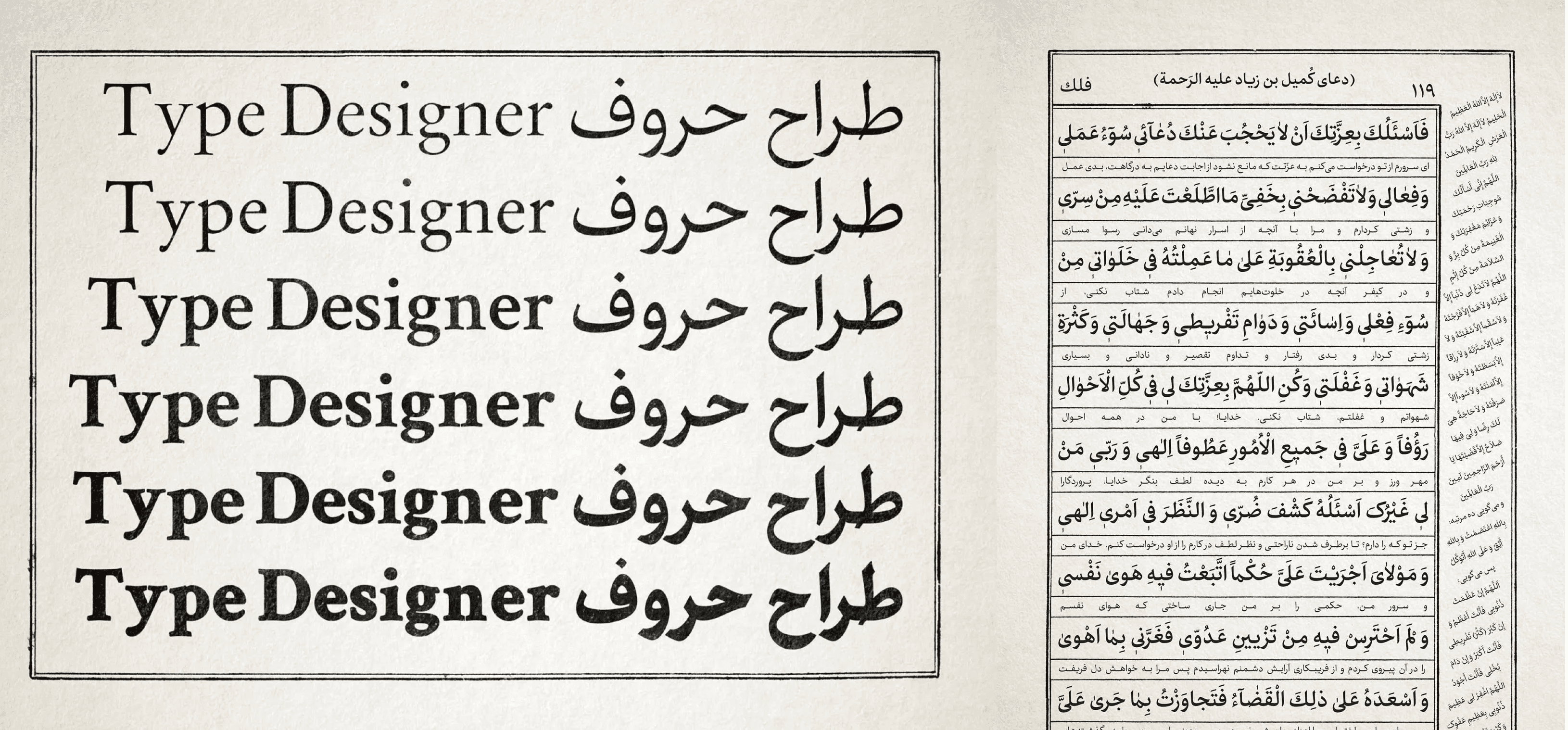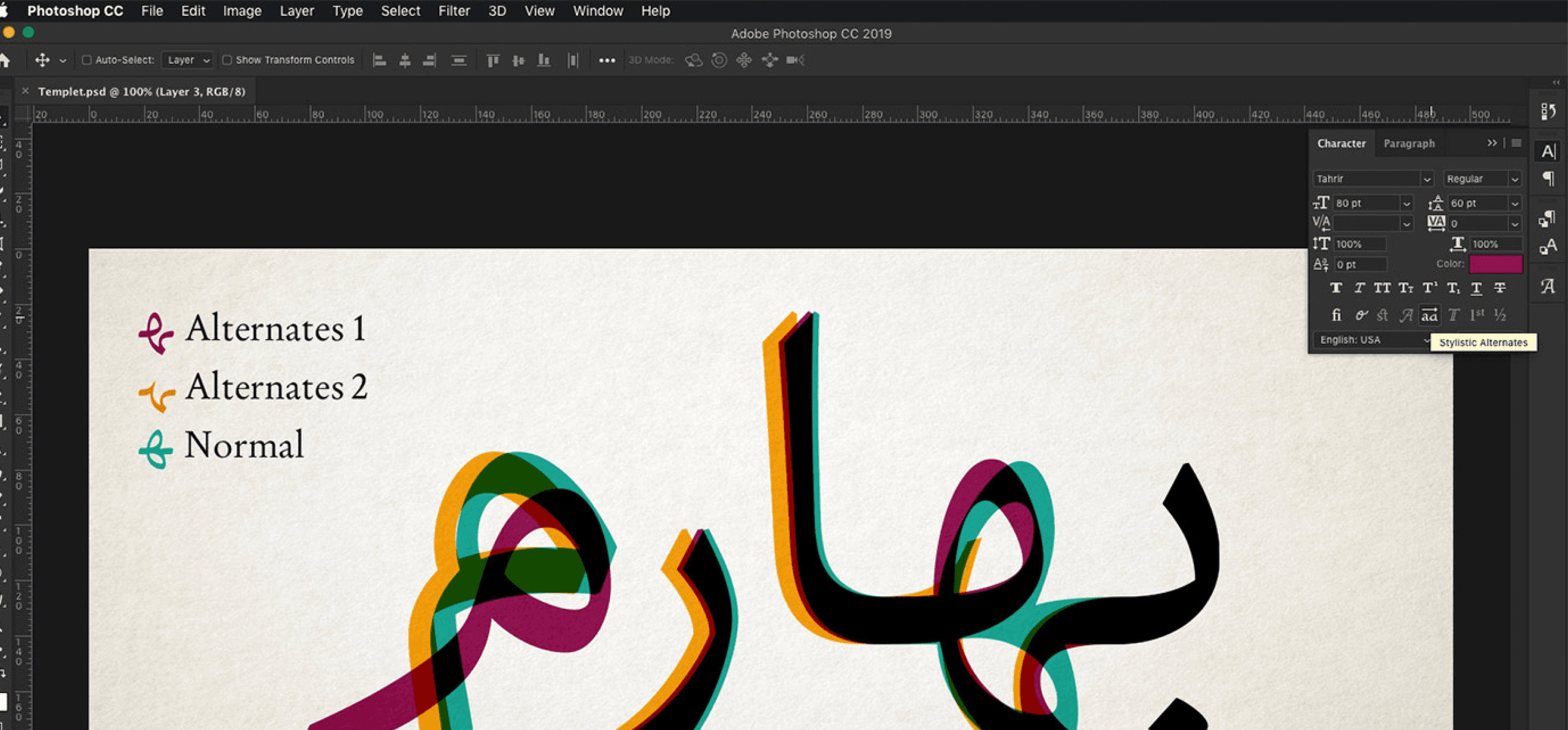
خط "تحریر" هو خط نص فارسي وعربي صُمم اعتمادًا على خط النسخ، ويتميز ببنية مألوفة ورسمية تتوافق مع خصائص الحروف المستخدمة في النصوص.
في تصميم خط تحریر، أُوليَت الأهمية لعنصري الجمالية والقراءة بنفس الدرجة، حيث تم استلهام الجاذبية البصرية من خط النسخ العربي، مع مراعاة النسبة المميزة بين الارتفاع والمساحة في النسخ الإيراني.
ونتيجة لذلك، يُقدَّم خط تحریر كوجهٍ جديد ومعاصر لخط النسخ المطبوعي.